El arte de crear tipografía en movimiento
La tipografía cinética, también llamada tipografía kinética, ha experimentado una evolución increíble en los últimos años. Se presenta destinada a transmitir un concepto a través de la animación de texto y es considerada una técnica de expresión que combina mensajes para comunicar un discurso sujeto a la interacción de las palabras y las letras. Se define como el arte de crear tipografía en movimiento. Gran parte de este éxito es debido a que muchas marcas han querido tener su identidad visual supeditada a un sistema cinético, adquiriendo el movimiento todo el peso corporativo.
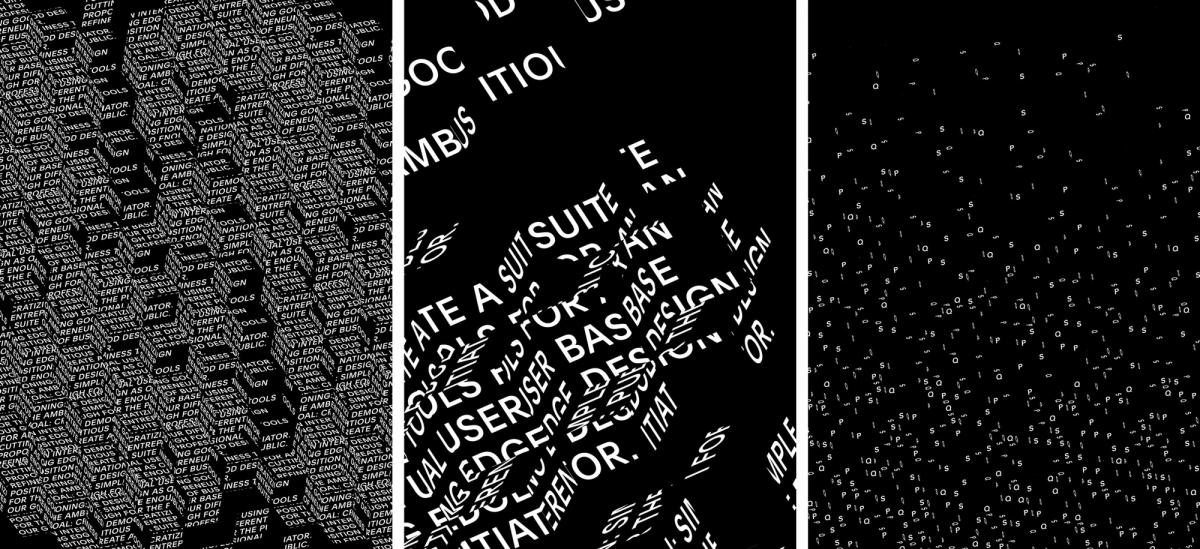
De todas formas, la tipografía cinética no está necesariamente vinculada a los medios digitales. Encontramos ejemplos de letras animadas ya en 1899 en el trabajo publicitario de George Melies en las que nos presentaba textos de manera secuencial y sometida a transiciones cinematográficas. La gran mayoría de largometrajes en esa época solamente contenían tipografía con texto estático y sin dinamismo. El gran cambio fue en la década de 1960 con la evolución del diseño de títulos de crédito en las películas. En esa época varios artistas comenzaron a emplear la tipografía como estrategia de comunicación usando el movimiento de las palabras. Uno de los pioneros fue Saul Bass que utilizó por primera vez esta técnica en la película de Alfred Hitchcock North by Northwest, empleando las letras en los créditos como elementos integrados y de interacción con la pantalla, evocando al espectador la energía intrínseca y el suspenso de la película. Saul Bass también recurriría a esta misma técnica en la película Psycho.
Hoy en día, tipografía cinética se utiliza principalmente para la comunicación digital. El interés por esta técnica se ha reavivado debido a la fácil disponibilidad y mayor accesibilidad de softwares de animación como Adobe After Effects tanto en círculos profesionales como simplemente en ámbitos de aficionados. Un estudio reciente estima un crecimiento de alrededor del 14.6% del video marketing cada año con la utilización de esta técnica para atraer a nuevos clientes. La mayoría de los videos son cortos, efectivos e informativos. Existen excelentes ejemplos de larga duración, pero por lo general los videos con tipografía animada se han forjado una reputación por ser breves y directos.
El buen uso de esta técnica hará conectar a la audiencia hasta el final del video. Es una excelente manera de resaltar puntos importantes de la marca, mostrar hechos significativos a través de las palabras y explicar a los usuarios todos los puntos esenciales de la idea a transmitir. Esto permite que las personas entiendan mejor el mensaje que el cliente está tratando de transmitir a su target. Facilita una comprensión total de los conceptos centrales de la marca y agiliza el proceso de decodificación. El éxito reside no solo en resaltar información, sino en procurar que el espectador vuelva a ver el video solo para observar el atractivo de la animación con el único propósito de convertir a los espectadores en potenciales clientes.
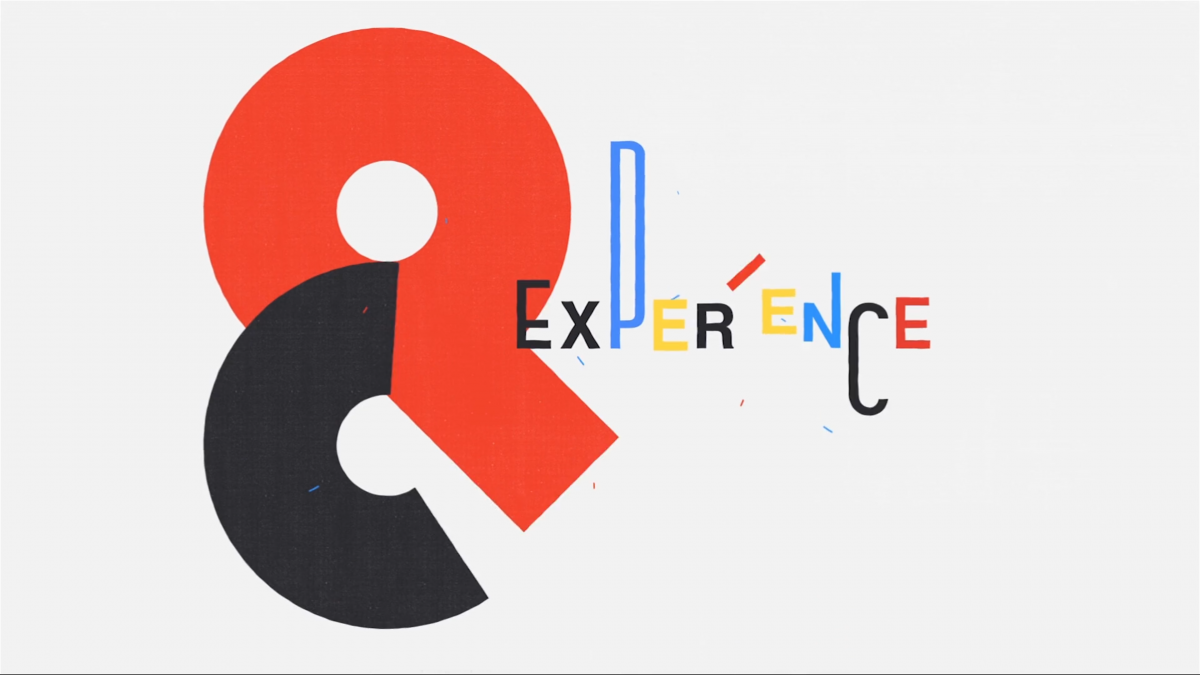
Las fuentes tipográficas influyen en la forma de percibir la información y elegir correctamente puede tener un efecto drástico en las personas y en como reciben los datos a través de texto animado. En la era digital actual la tipografía cinética es una revitalización contemporánea del uso de las fuentes. Afortunadamente, si no tienes instaladas en tu ordenador suficientes fuentes, existen infinidad de páginas online con paquetes de fuentes descargables gratuitas y de pago. Elegir la tipografía incorrecta podría dejar una impresión no deseada y reflejar un mensaje erróneo a la audiencia.
La principal intención es atraer la atención del espectador y obligarlo a rastrear visualmente las palabras que se mueven por la plataforma desafiando las convenciones del texto en horizontal. Las palabras pueden moverse por toda la pantalla, siendo los bordes el punto de referencia. El texto por sí solo es convencionalmente poco expresivo en comparación a otras formas gráficas de comunicación visual. La exploración de color, forma, tamaño, fuente y otros parámetros artísticos unidos al movimiento de las letras aumentan el poder expresivo del texto. El audio también puede ser usado para resaltar y mejora el poder expresivo de las palabras, dirigir sensaciones al espectador y enfatizar matices de la animación especialmente cuando se combina sonido y música.
En conclusión, la animación cinética se ha movido a la vanguardia de la comunicación visual por ser un método de expresión atractivo en comparación a otros formatos de animación. Es una técnica llamativa, estimulante, mejora la retención de mensajes, puede explicar conceptos de forma más sencilla y comunicar las ideas generales rápidamente. Se ha convertido en un recurso común en títulos de películas, anuncios de televisión y marketing digital para promocionar productos y generar resultados en redes sociales. La tipografía cinética contiene todos los factores para impresionar y con el tiempo se ha forjado como una herramienta imprescindible para las marcas.